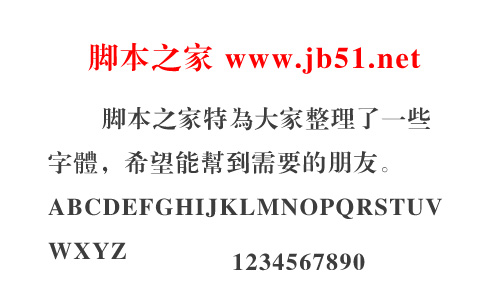
方正小標(biāo)宋繁體字體是方正字體庫中的一種字體,方正小標(biāo)宋源自1964年上海印刷技術(shù)研究所設(shè)計的標(biāo)題宋,是專門針對小字號標(biāo)題設(shè)計的,長期被廣泛用于“紅頭文件”的標(biāo)題。相對于方正大標(biāo)宋,方正小標(biāo)宋的筆畫略細(xì),中宮略為放松,筆畫飽滿平和,字形端莊穩(wěn)重,適用于人文類的文字標(biāo)題。喜歡的朋友們可以前來下載使用。